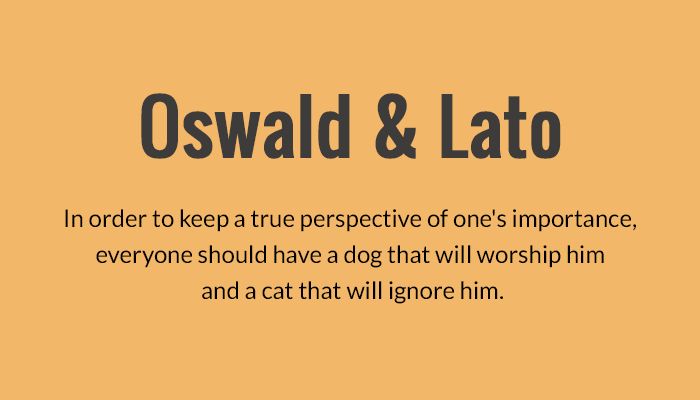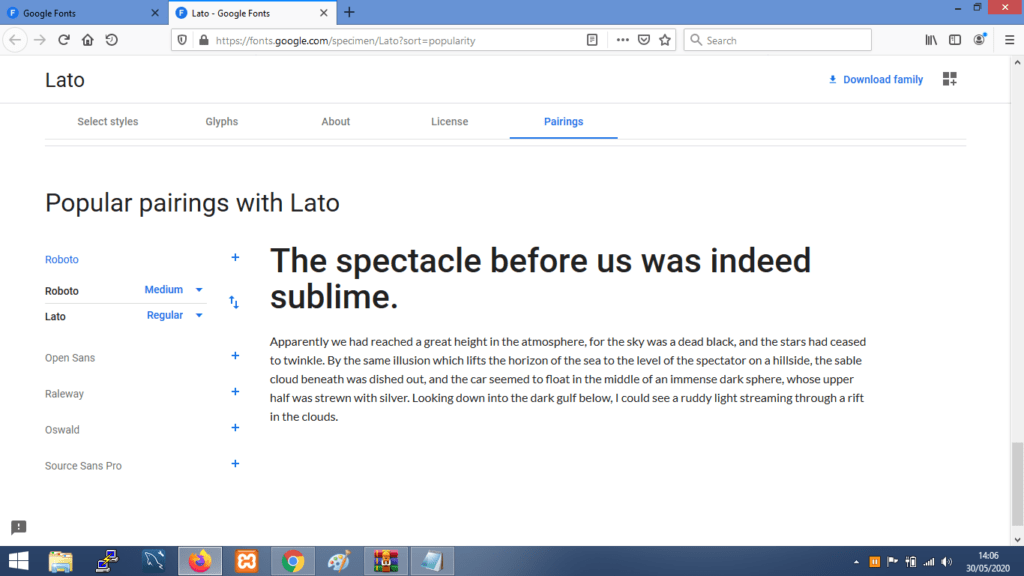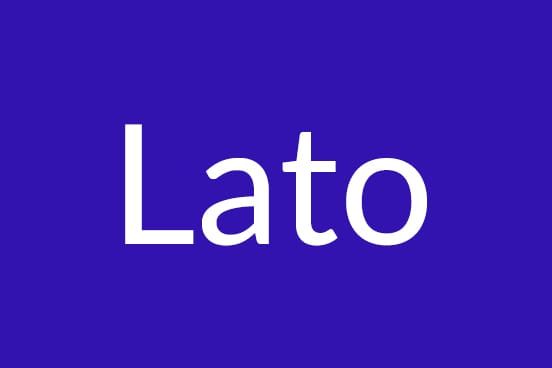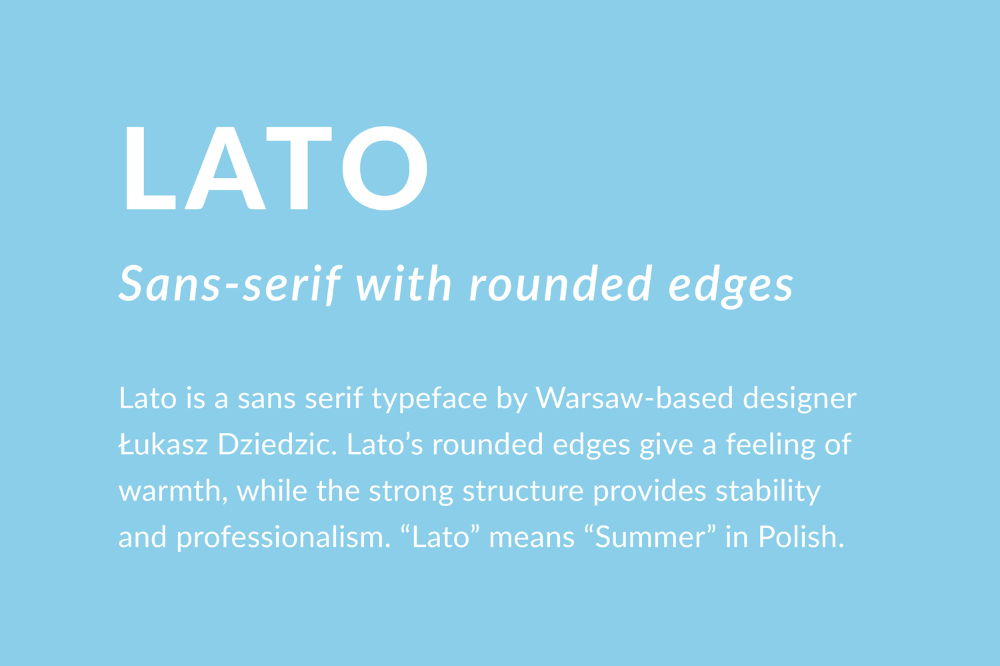
Посоветуйте Lato-похожий шрифт с кириллицей — Хабр Q&A
У нас были попытки переделать Lato и добавить кириллицу.
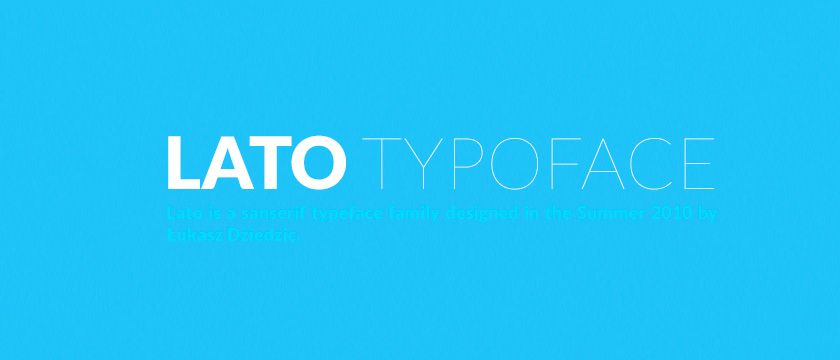
Шрифты, похожие на Lato, для использования в ваших потрясающих проектах
Цифровой дизайн стал неотъемлемой частью жизни людей.
Это касается как маркетинговых инструментов, так и веб-сайтов, которые мы посещаем ежедневно. Одним из наиболее важных элементов дизайна являются шрифты, которые сами по себе могут создать более удобный интерфейс. Благодаря большой популярности Google Fonts некоторые буквы стали стандартом в дизайне. Шрифт Lato является одним из самых популярных на сайте, поэтому для создания гармоничных изображений нам необходимы шрифты, похожие на Lato.
Lato заслужил сам по себе статус одного из лучших шрифтов, доступных на странице Google. Во-первых, не все становятся частью каталога Google Fonts; буквы должны соответствовать минимальному качеству. Семейство шрифтов Lato соответствует всем требованиям: быть удобочитаемым и адаптироваться к различным размерам.
Создан в 2010 году польским дизайнером Лукашем Дзеджичем по заказу корпорации. Однако некоторых творческих разногласий между заказчиком и Лукашем было достаточно, чтобы опубликовать типографику для всех.
В настоящее время Lato можно загрузить из Google Fonts в 18 вариантах толщины, каждый из которых имеет соответствующий курсив.
Также есть дополнительная версия с латинскими глифами. Все эти параметры делают его одним из самых универсальных доступных шрифтов.
Поскольку мы будем использовать его постоянно, хорошо иметь несколько шрифтов, похожих на Lato, которые позволят нам дополнить любой дизайн. Любой из следующего списка — отличный вариант для сопровождения.
8. Как удобочитаемость и разборчивость Lato по сравнению с другими шрифтами в этой категории?
При использовании в основном тексте латиница очень удобочитаема и разборчива. Даже при меньшем размере шрифта он четкий и легко читаемый благодаря чистому стилю. Тем не менее, важно помнить, что типографика является произвольной и что на удобочитаемость может влиять ряд элементов, включая цвет, контраст и расположение.